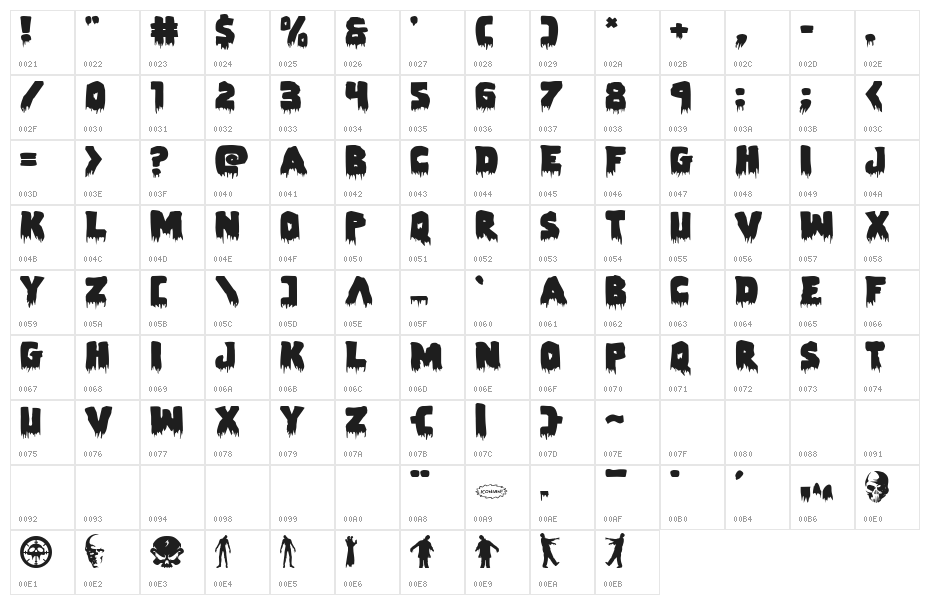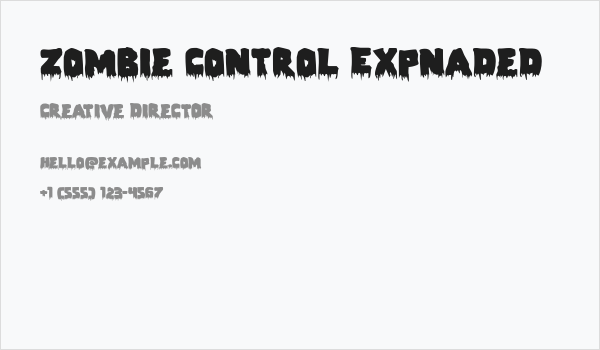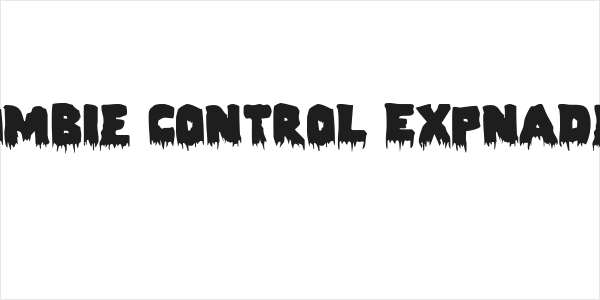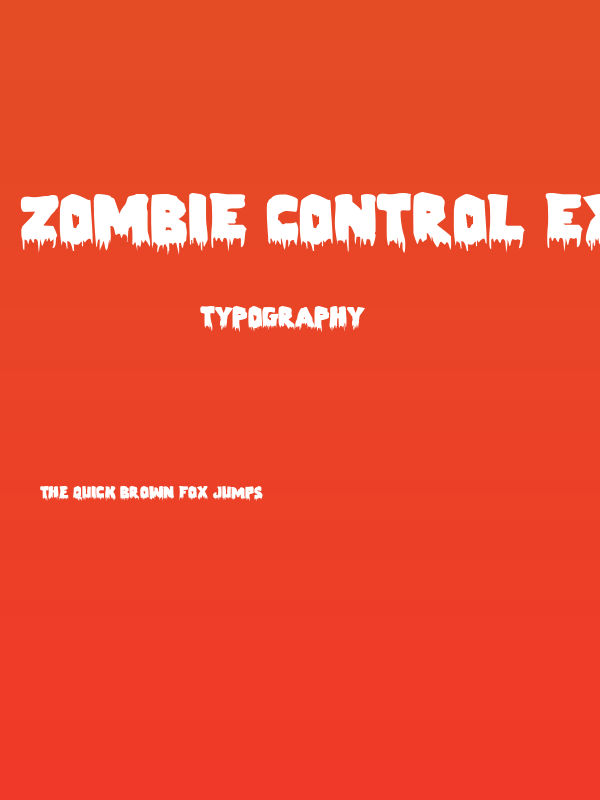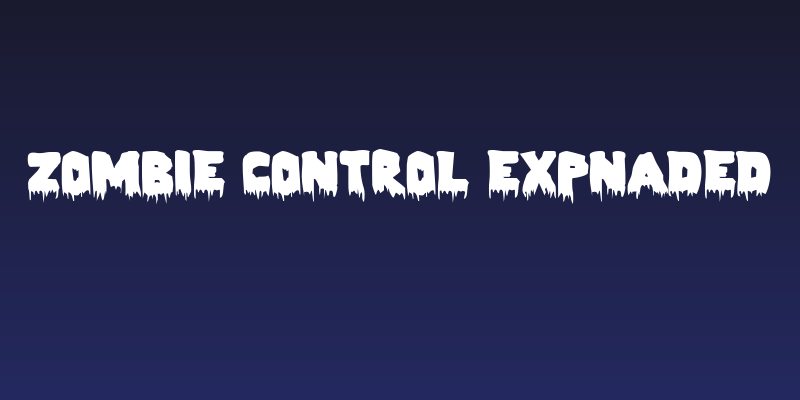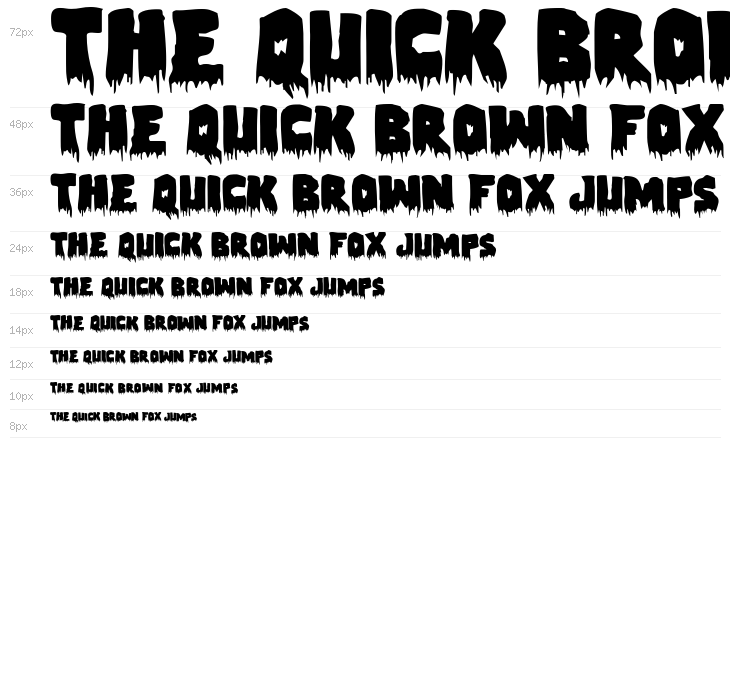
Zombie Control Expnaded Font
| Vorgeschlagene Projekte | Ideal for Halloween invitations, horror movie posters, haunted house flyers, and spooky-themed merchandise. |